Đối với các thủ thuật văn phòng, chắc hẳn các bạn đã biết cách cài đặt font chữ mặc định trên Word và Excel vô cùng đơn giản và dễ dàng. Nhưng đối với PowerPoint thì sẽ có nhiều cách để thay đổi hơn. Vậy cách mặc định font chữ trong PowerPoint 2010, 2013, 2019 như thế nào. Hãy cùng tìm hiểu bài viết này nhé!
Lưu ý:
- Bài hướng dẫn dưới đây sẽ giúp bạn biết cách cài font chữ mặc định trong PowerPoint. Việc thay đổi font chữ phù hợp cho slide sẽ giúp bài thuyết trình của bạn phù hợp với thời điểm, hoàn cảnh hay không gian buổi thuyết trình. Tăng sức thu hút của mọi người vào bài thuyết trình.
- Thủ thuật này được thực hiện trên phiên bản PowerPoint 2019. Các phiên bản 2010, 2013, 2016 và PowerPoint 365 thực hiện tương tự.
1. Cách cài font chữ mặc định trong PowerPoint
Cách 1: Đổi font chữ PowerPoint trong Slide Master
Bước 1: Vào View > Chọn Slide Master.
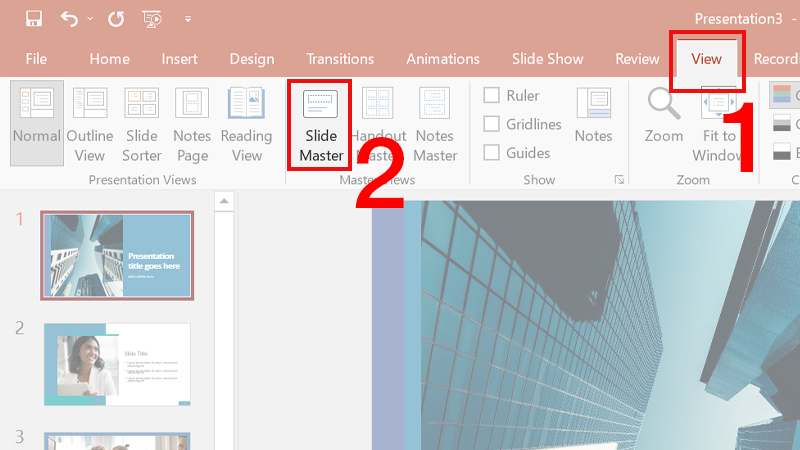
Vào View và chọn Slide Master
Bước 2: Chọn Slide đầu tiên > Nhấn Fonts trong mục Background > Chọn các Font chữ được thiết lập sẵn hoặc chọn Customize Fonts….
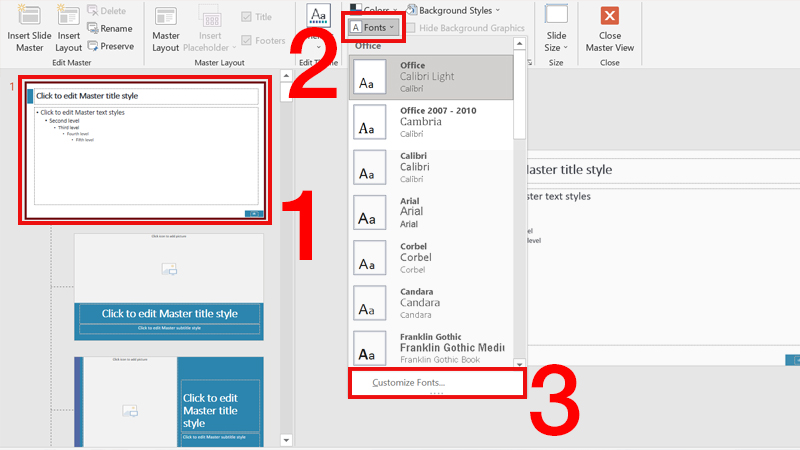
Chọn các Font chữ được thiết lập sẵn hoặc chọn Customize Fonts…
Bước 3: Trong hộp thoại Create New Theme Fonts chọn font trong mục Heading font và mục Body font > Tại mục Name đặt tên cho Theme > Nhấn Save.
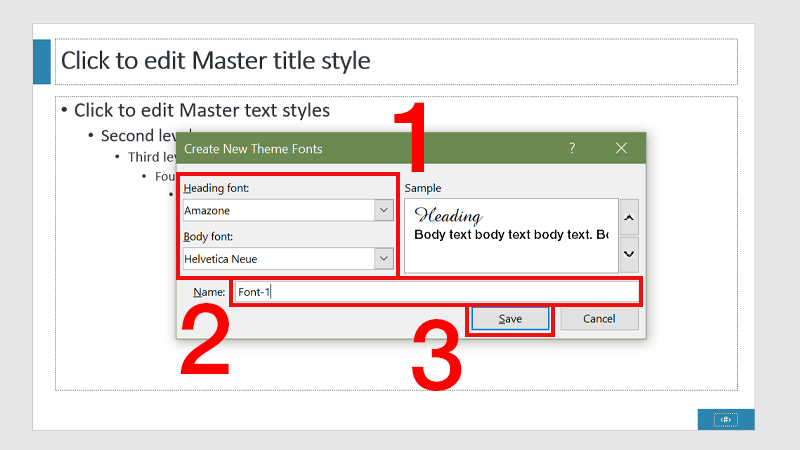
Chọn font cho phần Heading, phần Body và đặt tên cho Theme
Như vậy khi quay lại giao diện Slide Master bạn sẽ nhìn thấy font chữ vừa đặt tên khi vào mục Font.
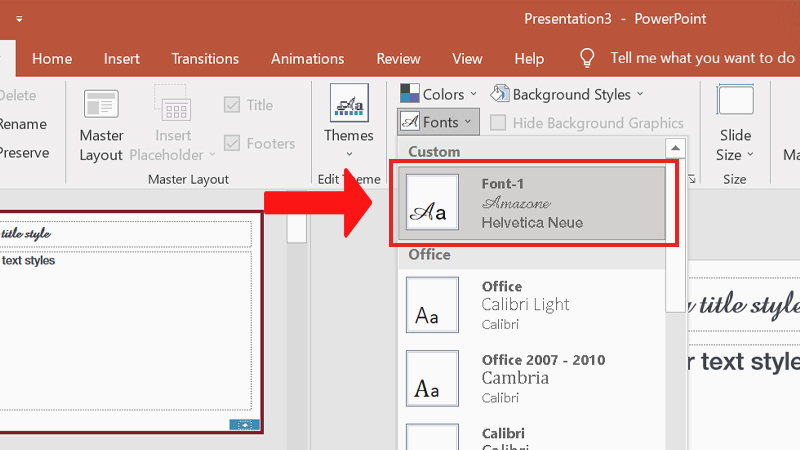
Font chữ vừa đặt tên nằm trong mục Font
Cách 2: Đổi font chữ PowerPoint trong Replace Fonts
Bước 1: Tại tab Home nhấn Replace > Chọn Replace Fonts….
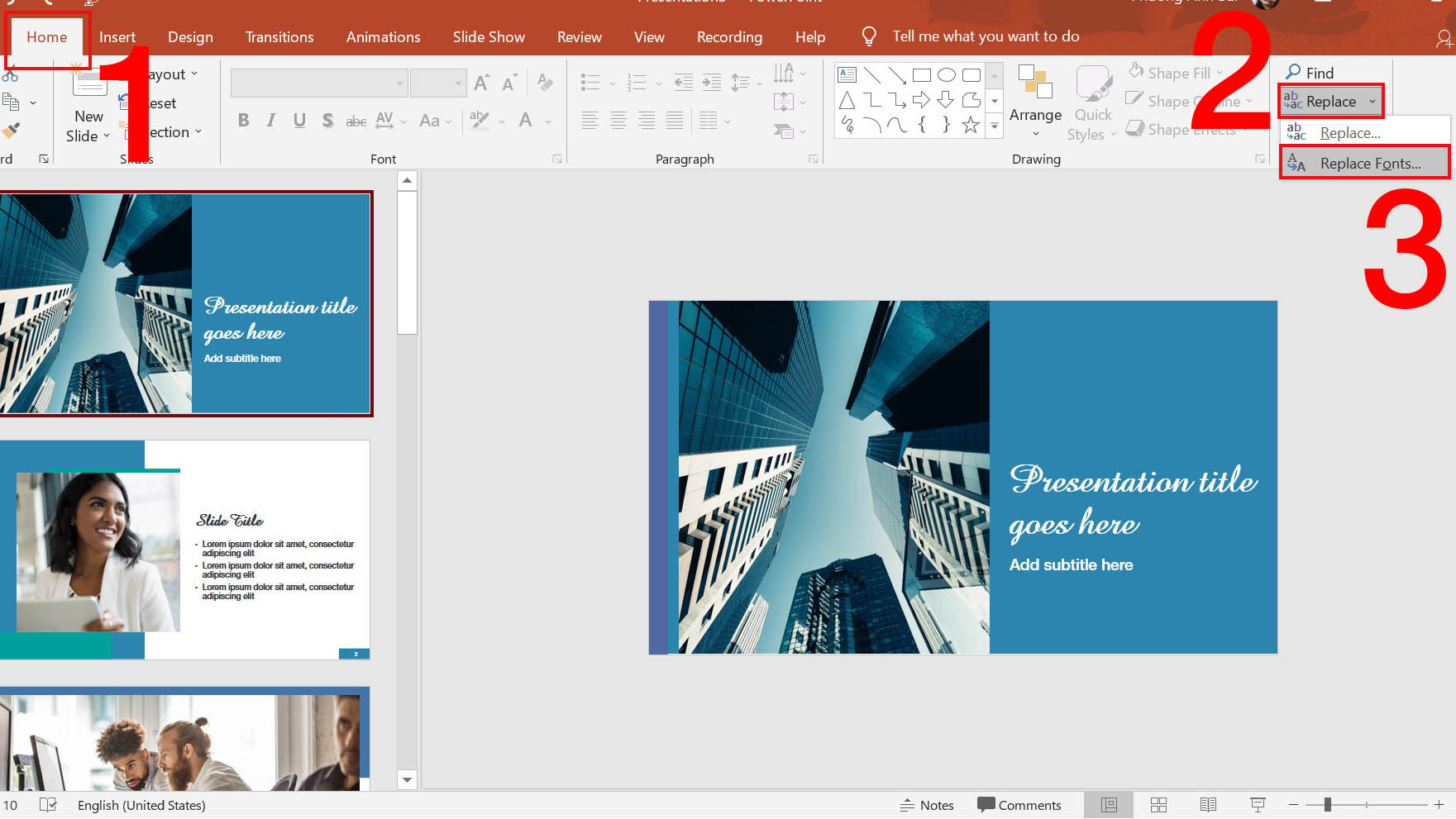
Tại tab Home nhấn Replace và chọn Replace Fonts….
Bước 2: Trong hộp thoại Replace Font ở mục Replace chọn Font muốn thay đổi > Tại mục With chọn Arial > Nhấn Replace để thay đổi.
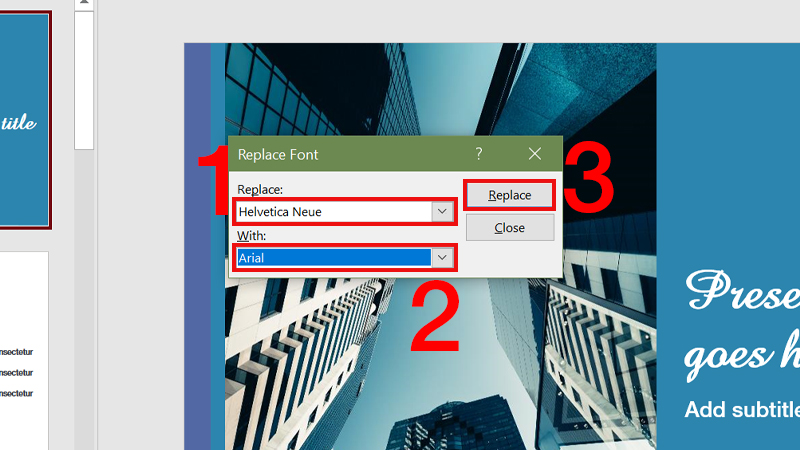
Chọn Font mới để thay đổi cho Font trước đó và nhấn Replace để thay đổi
Cách 3: Thay font chữ PowerPoint trên Text Boxes
Bước 1: Vào tab Insert > Chọn Text Box để tạo khung nhập chữ.
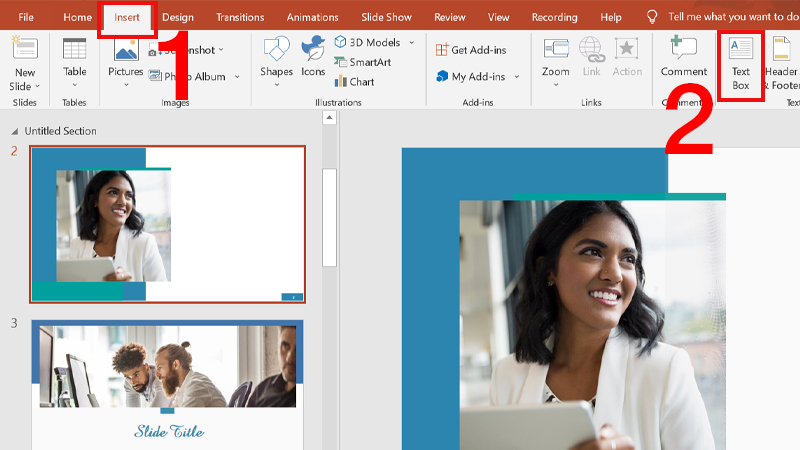
Vào tab Insert và chọn Text Box để tạo khung nhập chữ
Bước 2: Kéo khung vẽ văn bản rồi nhập nội dung văn bản bất kỳ > Chỉnh định dạng Font chữ như màu sắc, kích thước > Nhấn chuột phải > Chọn Set as Default Text Box.
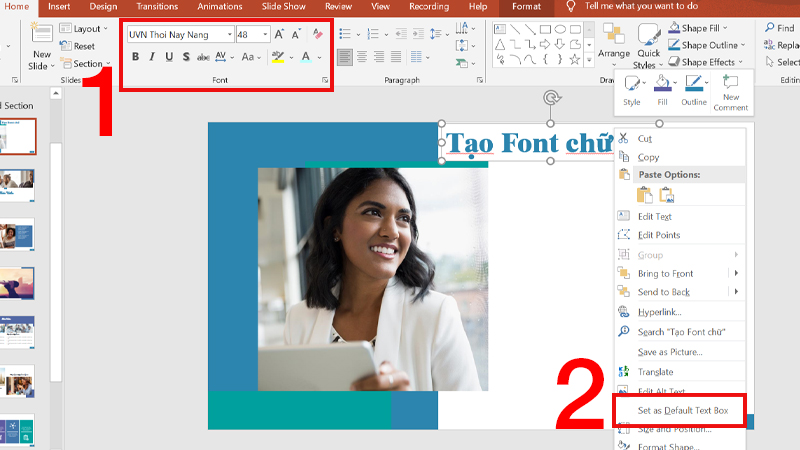
Nhập văn bản, chọn định dạng và nhấn chuột phải chọn Set as Default Text Box
Như vậy khi làm việc với các khung Text Box khác rồi nhập chữ thì định dạng chữ tự động được áp dụng cho nội dung mới.
2. Một số lưu ý khi cài font chữ mặc định trong PowerPoint
– Font chữ mặc định trong PowerPoint là Calibri tuy nhiên bạn có thể cài các font chữ khác cho các slide của mình như: Arial, Time New Roman,…
– Khi cài font chữ cho slide của mình, bạn cần lưu ý là có 2 loại chữ cơ bản: Chữ không chân (San Serif) như: Arial, Helvetica, Franklin Gothic,… Và chữ có chân (Serif) như: Time new roman, Garamond, Goudy Old Style,… Không nên cài font chữ có chân ở các đoạn văn bản nhỏ và dài, vì sẽ tạo cảm giác chữ bị dính vào nhau, gây rối mắt và khó đọc.
– Đối với thay đổi font chữ trên Text Box thì các font chữ ở ngoài Text Box sẽ không thay đổi.
Font chữ mặc định trong PowerPoint
3. Câu hỏi: Làm sao để lưu font chữ mặc định cho tất cả slide sau?
Để lưu lại Font chữ mặc định cho những lần tiếp theo bạn có thể thực hiện các bước sau:
Bước 1: Vào File > Chọn Save As > Chọn Browse.
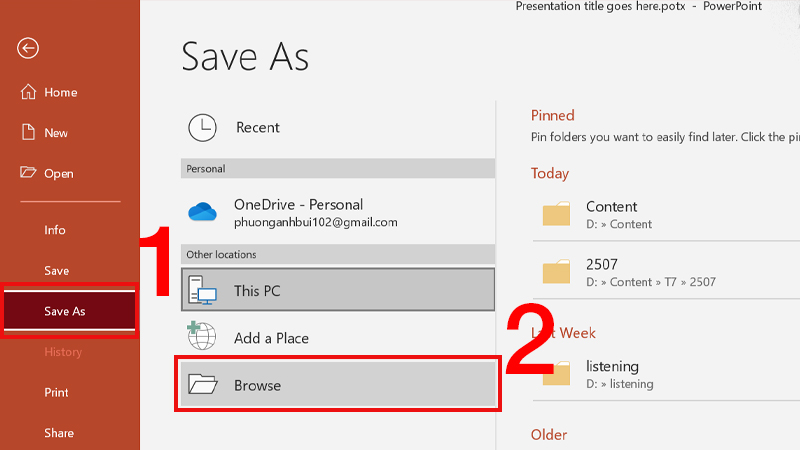
Vào File chọn Save As và chọn Browse
Bước 2: Trong hộp thoại Save As tại mục Save as type chọn PowerPoint Template > Nhấn Save.
Tại mục Save as type chọn PowerPoint Template và nhấn Save